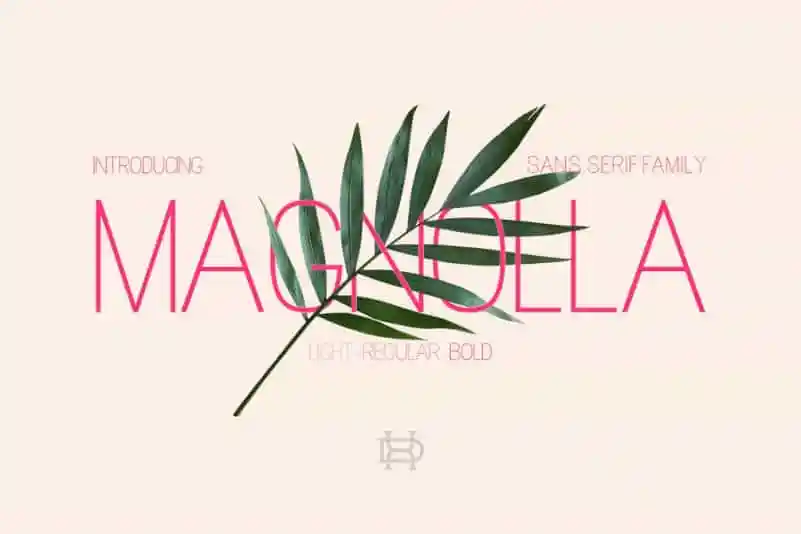
Magnolla Sans Serif Font – Download Grátis
Magnolla Sans Serif é uma nova adição à coleção das fuentes sans serif disponíveis para designers. Seu design moderno e fresco lhe dá um visual amigável, ao mesmo tempo renovado e único. Desenhada por dxsign na plataforma de criações 99designs, a Magnolla não apenas combina características de elegância e clareza, mas também oferece versatilidade para estilos modernos e robustos. Esta fonte é perfeita para um leque amplo de aplicativos. Suas linhas finas são ideais para logotipos, rótulos, vídeos, cartazes de casamento ou até mesmo impressões de embalagens de produtos. Também serve bem em websites, como parte do estilo único e diferenciado que o cliente deseja, além de ser uma excelente escolha para criações de moda, como desenhos de roupas ou detalhes para etiquetas de acessórios. Com Magnolla Sans Serif no seu arsenal de ferramentas de design, suas obras terão um visual fresco e moderno. Esta é a fonte ideal para qualquer projeto que você esteja trabalhando – seja uma nova marca em desenvolvimento, ou uma estratégia de branding renovada. A Magnolla oferece o ideal em simplicidade e elegância, tornando-a uma escolha ótima tanto para designers profissionais quanto para aqueles que estão apenas começando no mundo do design gráfico.